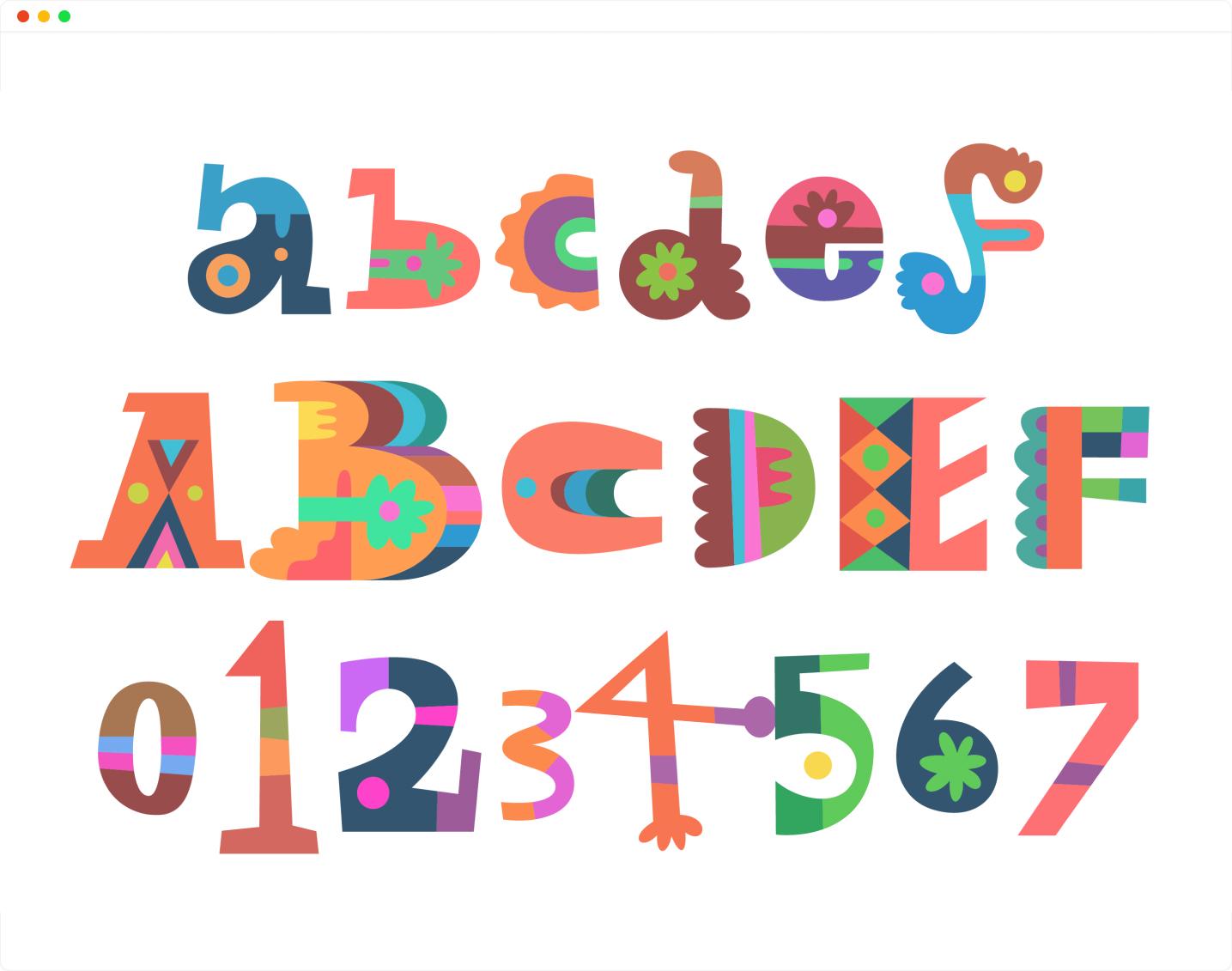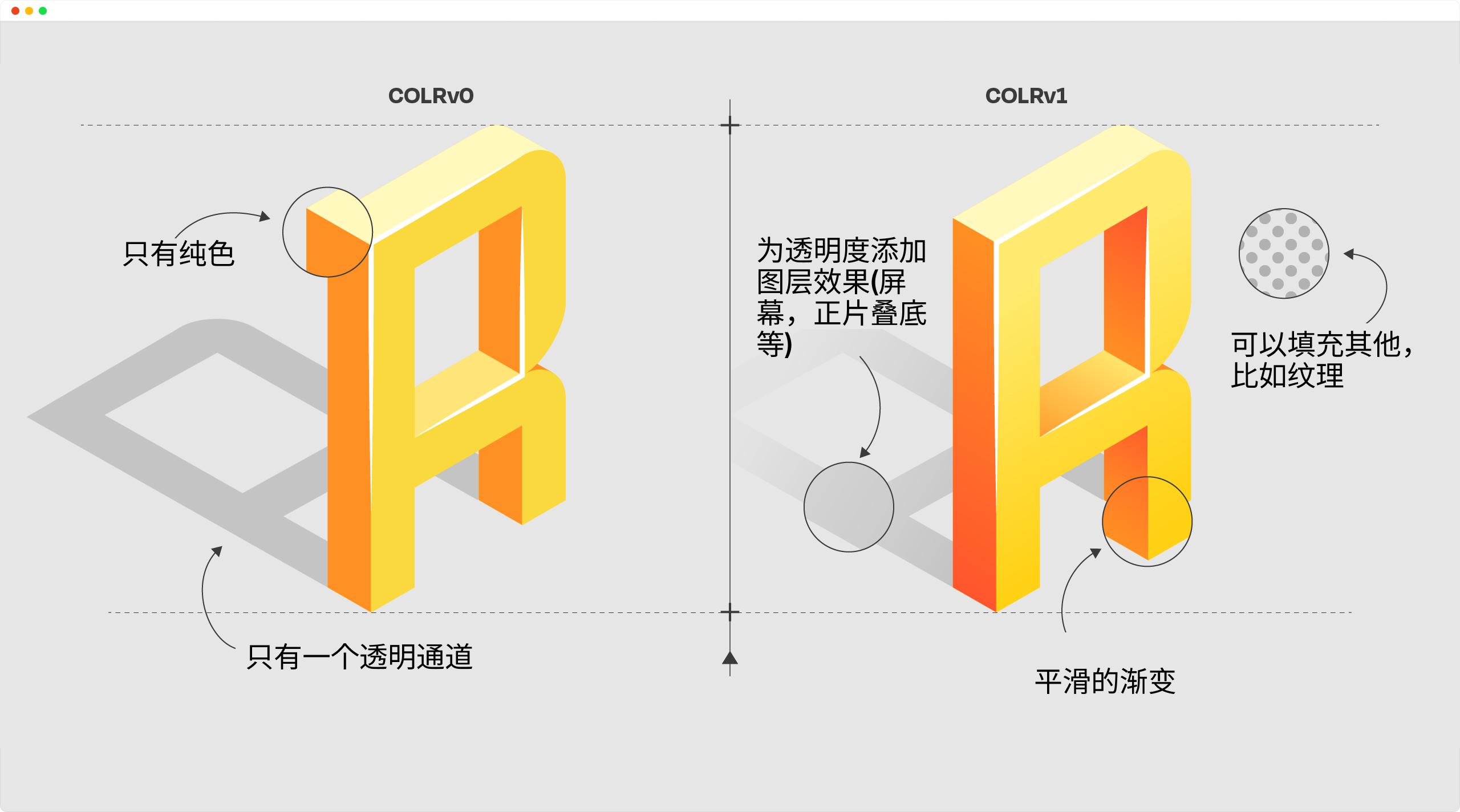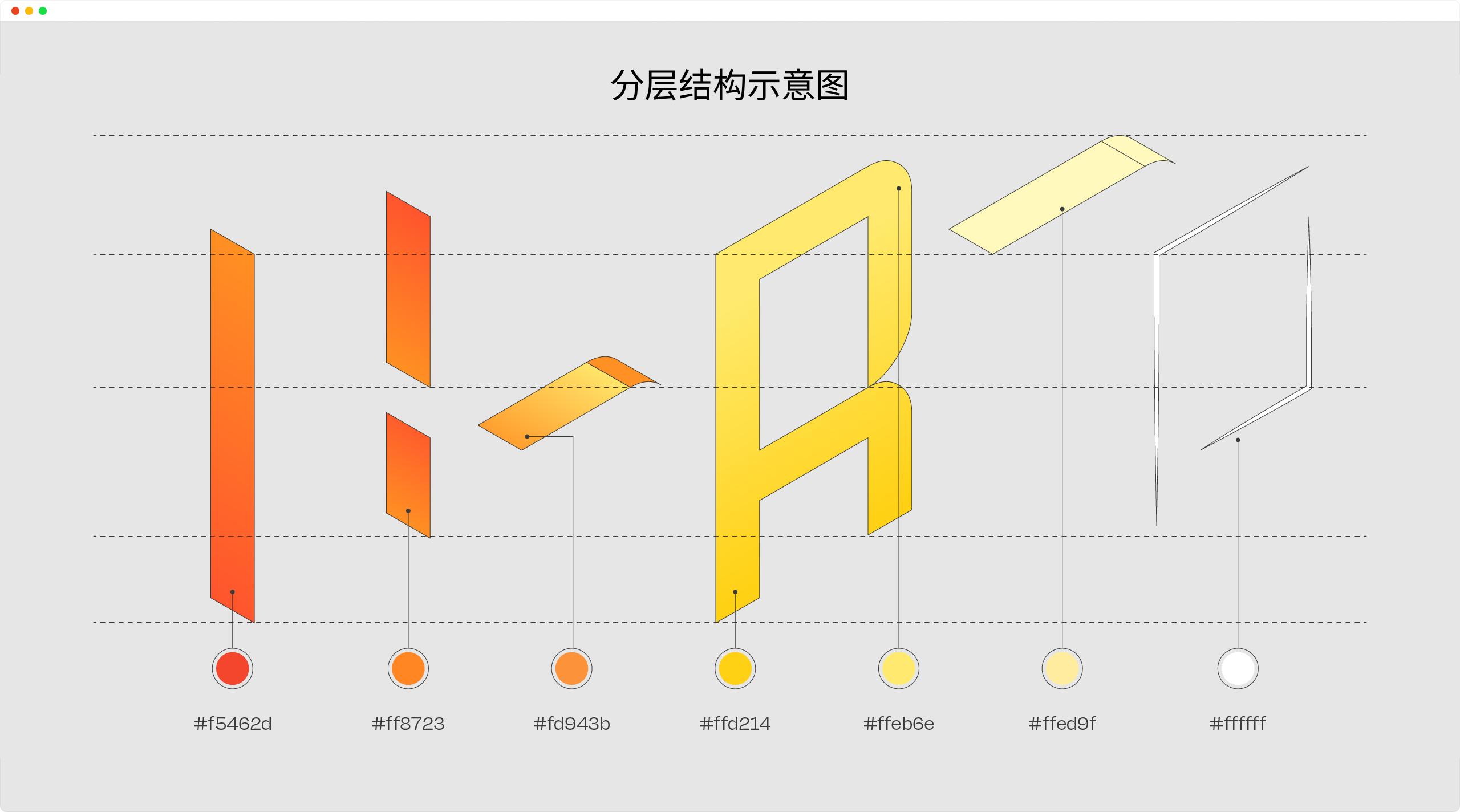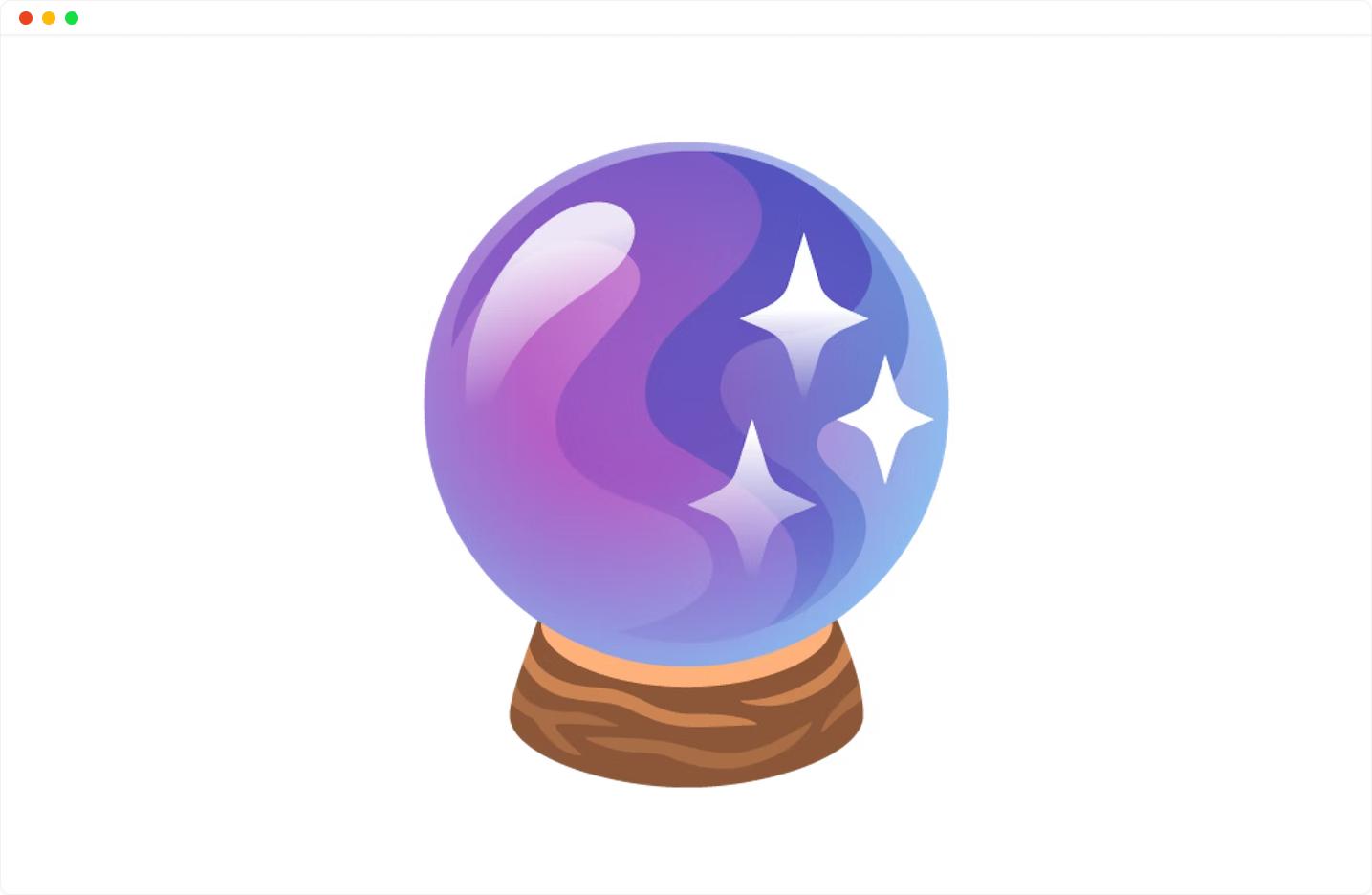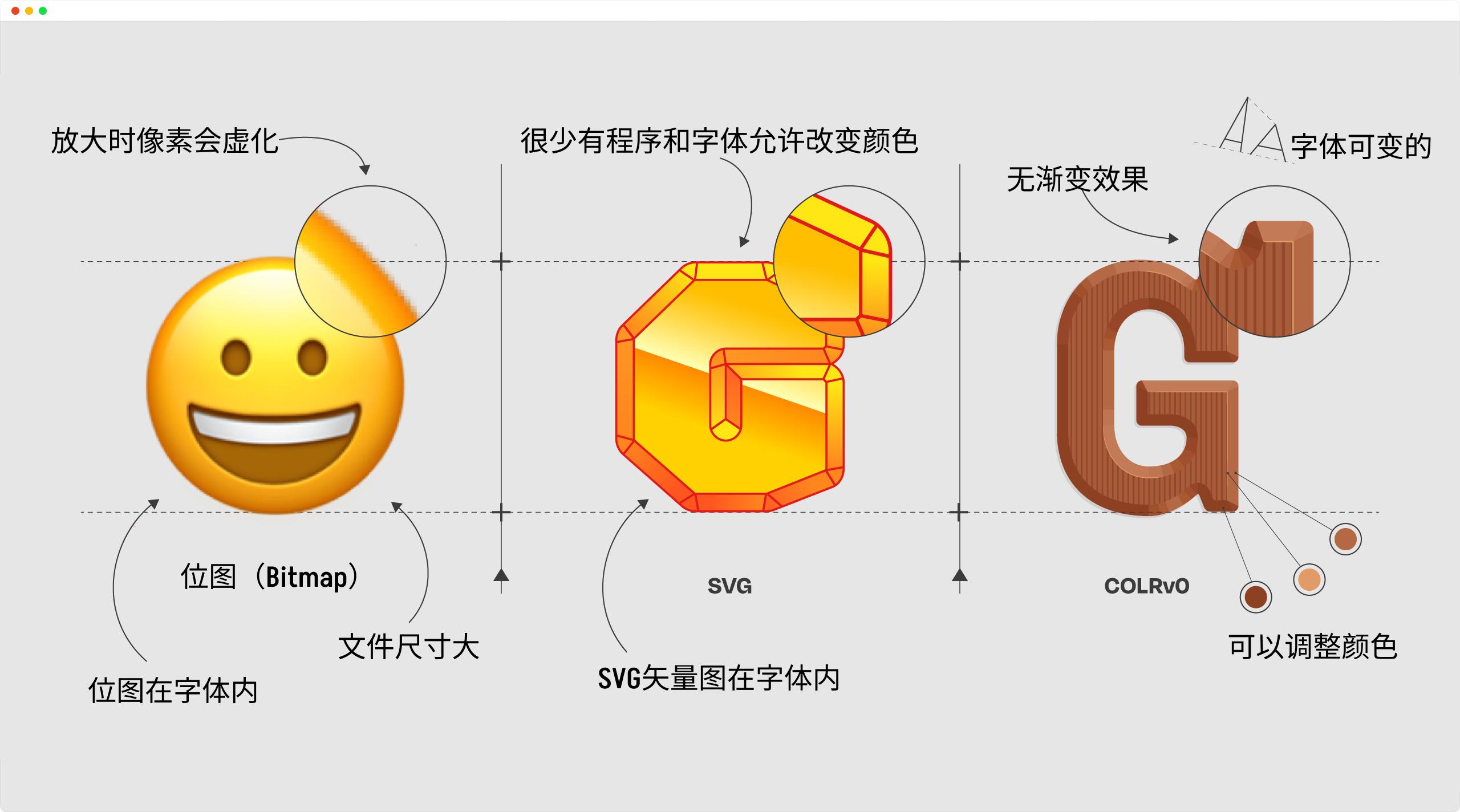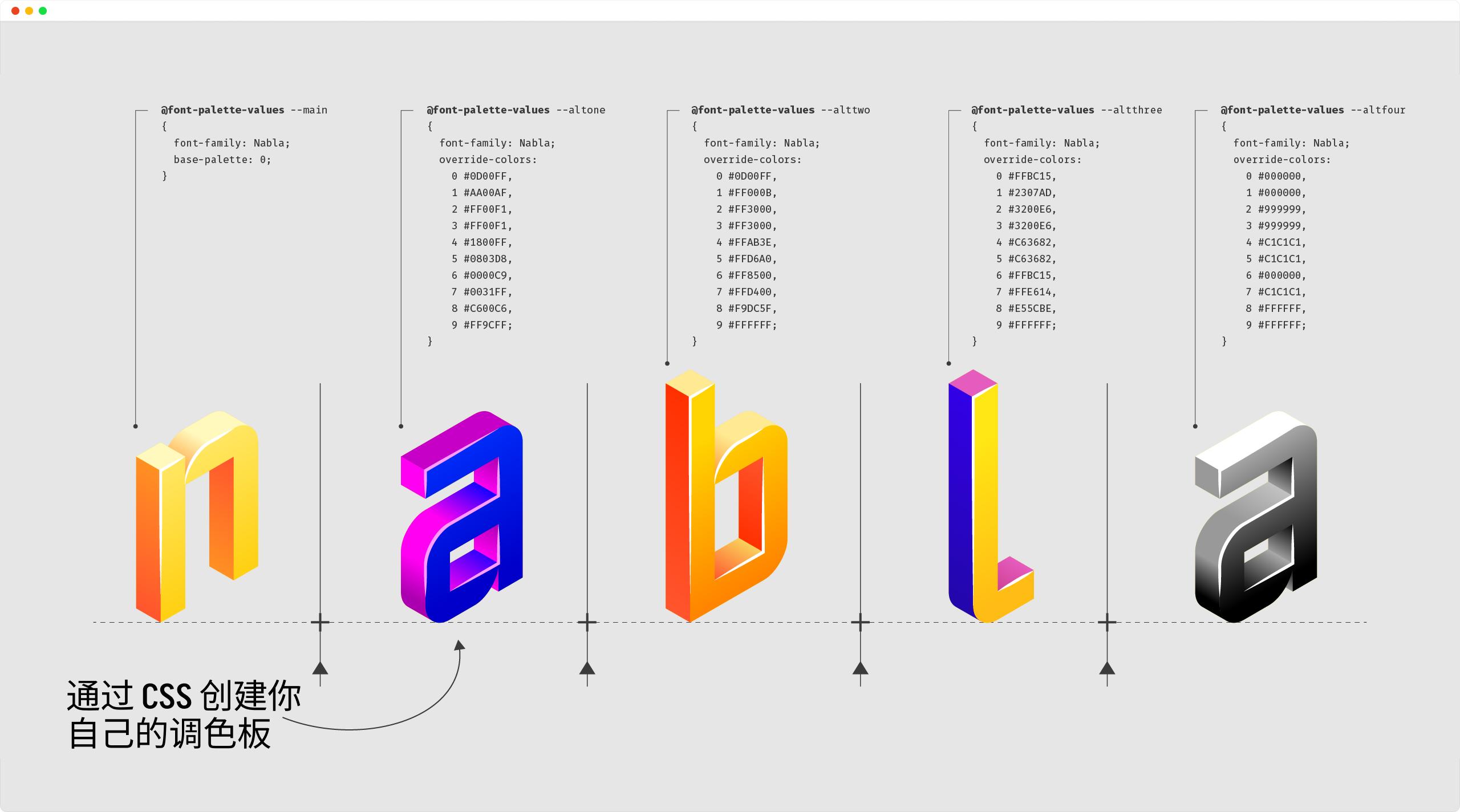
每位 Web 开发者都知道如何设置文本颜色,对吧?这是我们开始学习 CSS 时做的第一件事之一。我们可以使用 CSS 的 color 属性给文本设置颜色,例如 color: blue 或 color: purple ,这样在浏览器上呈现给用户的文本颜色将会是蓝色或紫色,且是一种纯颜色文本。但是,如果要给每个字形运用多种颜色,甚至是渐变色,那应该怎么办呢?
庆幸的是,随着 OpenType 彩色字体的出现,你可以很容易做到这一点。
如上图所示,它可能看起来像是在设计软件中设计的图片,但实际上你正在使用浏览器查看实时的、可编辑的、可搜索的文本。这些就是彩色字体,它使得每个字形具有多种颜色,而不是通过 CSS 控制它们的颜色,从而展示出相当惊人的效果。
也就是说,彩色字体提供了一种不牺牲使用纯文本所带来的诸多优势的情况下增加设计丰富度的方式,同时它也开辟了全新的排版创意。这也意味着彩色字体可以以一种新颖、有趣、具有表现力的方式呈现文本,让 Web 设计师有更多创意自由度来表达信息和情感。
随着新增的 CSS 特性(包括 font-palette 属性和 @font-palette-values 规则)可用来控制彩色字体的颜色调色板以及 COLR 字体格式等。彩色字体已经成为许多 Web 设计师和开发人员的首选,因为它们不仅在 Web 和APP 开发中提供更多的视觉创造空间,而且能够有效改变文字的情感和表达。
换句话说,现在是深入研究并尝试使用彩色字体的时候了。在这节课中,将和大家一起深入探讨了彩色字体的操作方式以及如何在 Web 设计中利用和自定义它们。
为什么要使用彩色字体?
在 Web 上,文本通常以 CSS 中的 color 属性值来指定颜色。字体本身并不定义任何特定的颜色,它只描述字体外形的特征。这本是件好事。CSS 可以让 Web 开发者更灵活的为文本指定颜色。然而,有时一个字形包含多个颜色,它们是有意义的。例如,Web 设计师想在某些特别的专题活动中使用下图的字体作为标题展示:
如果仅以当前文本颜色简单绘制,则无法传达相同的含义。如果不这么做,则很多时候需要将其制作成图片的方式,然后在 Web 上呈现给用户。如此一来,你可能会遇到这几个问题:不同屏幕下的适配,要是只做一种尺寸的图片,放大或缩小后的效果都不太好。直接做成 SVG?好像不能复制到文本编辑里之类。也就是说,这种做法使得这些“文本”本身失去了真实文字该有的功能。
此时,彩色字体的好处就显现出来了。既能达到视觉效果上的要求,还拥有常规文字的功能,能够复制,能够粘贴,还可以被屏幕阅读器阅读,丝毫不妨碍常规操作。
什么是彩色字体?
在我们所熟知的传统字体中,字体文件本身仅仅描述了字体的外形特征,这些特征一般包含着矢量的轮廓数据或是单色调位图数据。在浏览器渲染单色字体时,渲染引擎使用设定的字体颜色填充字形区域,最后绘制出对应文字及其设定的颜色。而彩色字体中,不仅仅存储了字体的外形特征,还保存了颜色信息,甚至还能在字体中提供不同的配色,增加了灵活性的同时也更具丰富的外形细节。
简单地说,彩色字体是一种字体,包含多种颜色、阴影、纹理和透明度。它们可以在排版中呈现更加复杂和具有视觉吸引力的效果,为平面设计带来了新的创意和表现力。彩色字体可以包含矢量形状、位图图像或两者的组合,全部存储在字体文件中。彩色字体被认为是平面设计中的一大趋势,尤其是 COLRv1 的到来。
如今,对于大多数用户来说,表情符号是他们看到的唯一彩色字体。例如在 Windows 10 上,Segoe UI Emoji 就属于一款彩色字体:
通常彩色字体还会包含一些兼容信息,这些兼容信息包含 Unicode 编码的单色字形数据,使得在一些不支持彩色字体的平台上,仍然能够像渲染普通字体一样将彩色字体的字形渲染出来,达到一种向后兼容的效果。
彩色字体的类型和实现标准
在彩色字体设计的发展历史上,由于各家有自己的实现方案,导致在 OpenType 字体中嵌入的色彩信息标准也不尽相同。在最新的 OpenType 标准中,就有多达四种彩色字体数据的描述格式。
- SVG,由 Adobe 和 Mozilla 主导的矢量字体标准。其中不仅包含了标准的 TrueType 或 CFF 字形信息,还包含了可选的 SVG 数据,允许为字体定义颜色、渐变甚至是动画效果。SVG 标准中的配色信息也将存储在 CPAL 中。
- COLR + CPAL,由微软主导的矢量字体标准。其中包含 COLR 即字形图层数据和 CPAL 配色信息表,对其的支持集成在 Windows 8.1 及之后的版本中。
- CBDT + CBLC,由 Google 主导的位图字体标准。其中包含了 CBDT 彩色外形位图数据和 CBLC 位图定位数据,对其的支持集成在 Android 中。
- SBIX,由 Apple 主导的位图字体标准。SBIX 即标准位图图像表其中包含了 PNG、JPEG 或 TIFF 的图片信息,对其的支持集成在 macOS 和 iOS 中。
这也造成不同的浏览器采用了不同的标准:
| Microsoft Edge | Chrome | Firefox | Safari | |
|---|---|---|---|---|
| SVG(SVG-in-Opentype) | ✔ | ✘ | ✔ | ✘ |
| COLR + CPAL | ✔ | ✔ | ✔ | ✔ |
| CBDT + CBLC | ✔ | ✔ | ✘ | ✘ |
| SBIX | ✔ | ✔ | ✘ | ✔ |
由于这些格式的差异和不兼容性,设计行业正在经历一段过渡期,在这个过渡期中,可能需要几种彩色字体格式来确保跨多个操作系统、浏览器和应用程序的兼容性。
就彩色字体而言,到目前为止主要分为三种类型:位图、SVG 和 COLR 彩色字体。
其中:
- 位图彩色字体是使用像素绘制的,可以创造出任何你想要的形状。但它的缺点是这些字体的颜色无法更改,也不能放大到大尺寸,不然会产生失真的现象(像素虚化),另外其字体文件尺寸较大
- SVG 彩色字体是基于向量的,因此可以缩放,并且不会丢失质量(不会像位图彩色字体那样,放大时失真)。但它的缺点是颜色无法更改,并且不能制作成可变字体
- COLR 字体结合了位图和 SVG 彩色字体的优点,它是可变的,而且颜色也可以调整
COLRv0 和 COLRv1
所有浏览器都支持 COLR 字体,到目前为止,COLR 字体分为 COLRv0 和 COLRv1 两种:
如上图所示,COLRv0 仅支持纯色以及只有一个透明通道。虽然支持字体变化是一个很大的优势,但视觉效果方面的范围较小,限制了其潜力。
COLRv1 则有所不同,它允许你使用渐变(例如线性、径向或圆锥形渐变)、混合模式(例如屏幕、正片叠底等)和合成等功能设计字体,而且还允许你使用其他绘制的形状(例如纹理)来填充字形。例如:
COLRv1 比 COLRv0 更好的地方
COLRv1 是 OpenType 1.9 标准的一部分。虽然最初的 COLRv0 缺乏 OpenType-SVG 的许多创意可能性,但 COLRv1 却要比 OpenType-SVG 更胜一筹。正如排版专家 @Roel Nieskins 所说:
“我曾经说过 OpenType-SVG 格式是最好的格式,因为它提供了最多的多用途性,直到我意识到这对于像文本渲染这样的低水平工作来说太复杂了。它在字体渲染级别上实现了SVG 的基本子集,但它与其他字体技术(提示、可变轴等)不兼容,并且实现起来很麻烦。所以,我转向了COLR。COLR 基本上重新使用了 OpenType 字体已经拥有的一切。它“仅”添加了分层和更改每个图层颜色的可能性。简单但有效。”
COLRv1 与可变字体轴完全兼容,已经有许多变量 COLR 字体的示例,例如 Merit Badge、Plakato Color 和 Rocher Color。
简单地说,COLRv1 是一种新的字体格式,支持多种不同的颜色方式,但这些方式都存在不同的权衡。我们希望COLRv1 的图形能力和紧凑文件的组合将使其成为许多彩色字体应用实例的不错选择。COLRv1 增加了渐变、合成和混合,并改进了内部形状重用以获得更紧凑的文件。
COLRv1 的表现能力与 SVG Native 加上混合和合成功能相当。它有四种类型的颜色填充: 纯色、线性渐变、径向渐变和锥形渐变。COLRv1 允许您使用完整的平移、旋转、切变和比例变换重新定位和转换字形元素。此外,它还支持字体变体,并重用字体中现有的形状定义格式。
以水晶球表情符号为例:
星形的亮点形状相同但大小不同,这意味着只需一个形状即可在文件内重新定位和重复使用,而无需重复编码每个形状以用于每个字形。该格式允许你在新的字形内重复使用全部字形,而无需为每个字形冗余地编码相同的形状。想象一下一个有花卉装饰的装饰性彩色字体,其中只需引用现有的彩色字形即可将同一花朵形状放置在不同的字母上。对于 Web 字体用例,COLRv1 在 woff2 下压缩效果良好。例如,使用 COLRv1 构建的 Twemoji 测试版本在解压后约为1.2MB,但在 woff2 格式下约为 0.6MB。完整的 Noto Emoji Glyp 字形集从位图版本的 9MB 缩减到了COLRv1+woff2 格式下的 1.85MB。
尽管如此,让我们更深入地了解其关键属性以及它们如何为用户和字体创建者带来价值。
- 预定义和可自定义调色板:如前所述,COLRv1 彩色字体具有内置的颜色调色板,我们可以调整它们以匹配所需的项目外观和感觉。这使得设计师对其文本的整体外观有更多的控制。
- 高保真度渲染:COLRv1 使用基于矢量的光栅化来提供高质量的渲染。这确保字形在所有尺寸下保持锐利和清晰。
- 轻量级:与 COLRv0 字体不同,COLRv1 字体更加轻量级,不会膨胀文件大小。这使得它们非常适合在需要考虑文件大小的 Web 和其他情境中使用。
COLRv1 彩色字体是如何工作的?
在 COLR 字体文件中,包含了各种轮廓形状,每个形状分配有颜色、渐变或混合模式。在导出为字体时,这些层被组合为一个单独的字符,可以通过键盘进行访问。因为颜色是从最高层的“颜色表”为形状分配的,不像 SVG 字体那样嵌入到它们内部,所以可以通过代码更改颜色值,并使用字体变量转换形状。
如何自定义 COLRv1 ?
目前没有桌面应用程序支持 COLRv1 字体,而只有少数应用程序支持 COLRv0。但是,在 Web 上,COLR 规范运行良好。与其他彩色字体版本相比,COLR 字体的文件大小很小,通过 CSS,可以逐个颜色地调整颜色板。网页的进一步可能性提供了可变字体变化和动画的可能性。想要自己尝试一下吗?你可以在此处找到有关自定义颜色板的更多信息,以及有关可变动画的更多信息。
如上图所示,在图中示意的代码中,出现了几个你可能不太熟悉的 CSS 属性和 @ 规则,例如 base-palette 、override-colors 和 @font-palette-values 等。在 CSS 中,我们可以通过这些属性和规则来使用彩色字体。
小结
当然,有权力就应该有责任,仅仅因为你可以更改颜色,并不意味着你总是应该这样做。通常,调色板中的颜色是协调美学上的相互关系,因此有必要了解它们应该如何相互关联。你可以查看字体的预定义颜色调色板,以了解字体设计师分配调色板中每种颜色的角色,然后进行微调。
选择与背景形成强烈对比的颜色也是非常重要的,以保持你的文本可读性和网页可访问性。字母基础色调色板中使用的颜色通常应该在背景上突出显示,而像阴影、轮廓和装饰元素之类的支持层可能会更少地对比以保持从不压倒字形。
彩色字体比图形图像更有改进之处,因为它们默认情况下与屏幕阅读器、复制、粘贴和页面查找一起使用。此外,如果字体无法加载,它们会优雅地显示备用文本,并且如果浏览器窗口大小调整,则可以重新流动。不仅如此,彩色字体比图形图像更灵活,因为它们可以将使用它们的元素的前景色融入字体的设计中。
彩色字体并不意味着取代单色字体。但是在适当的情况下以适当的大小使用时,它们可以是完美的锦上添花!
随着越来越多的可变字体和彩色字体的出现,网页排版正朝着丰富的定制和创造性表达的方向发展。它们为网页设计提供了新的表现力和创造性,可以使你的网站脱颖而出。